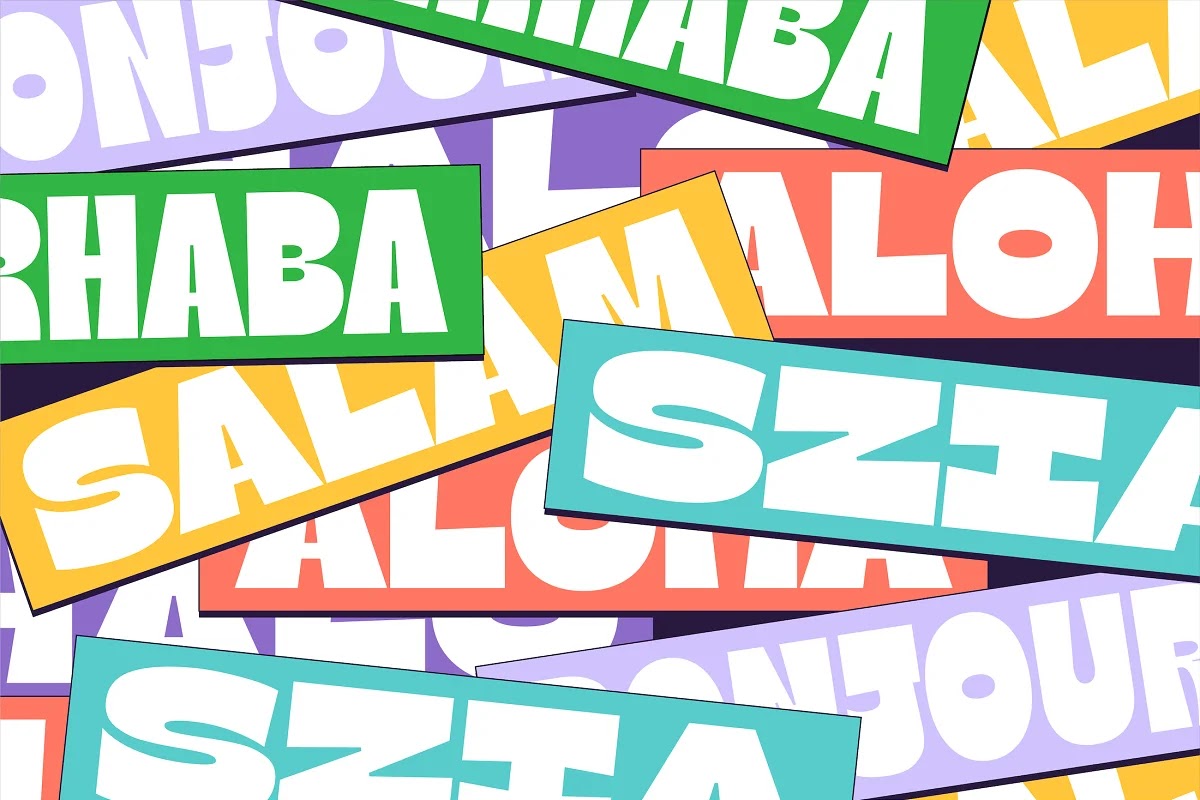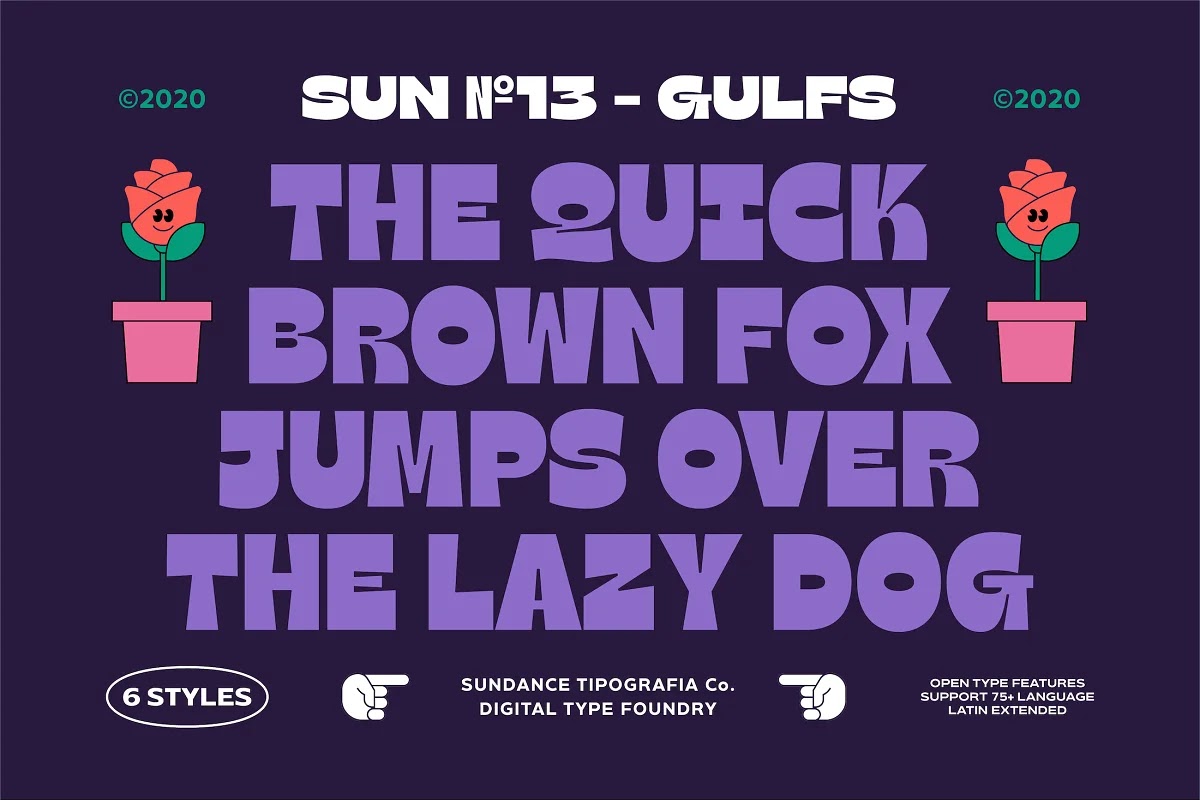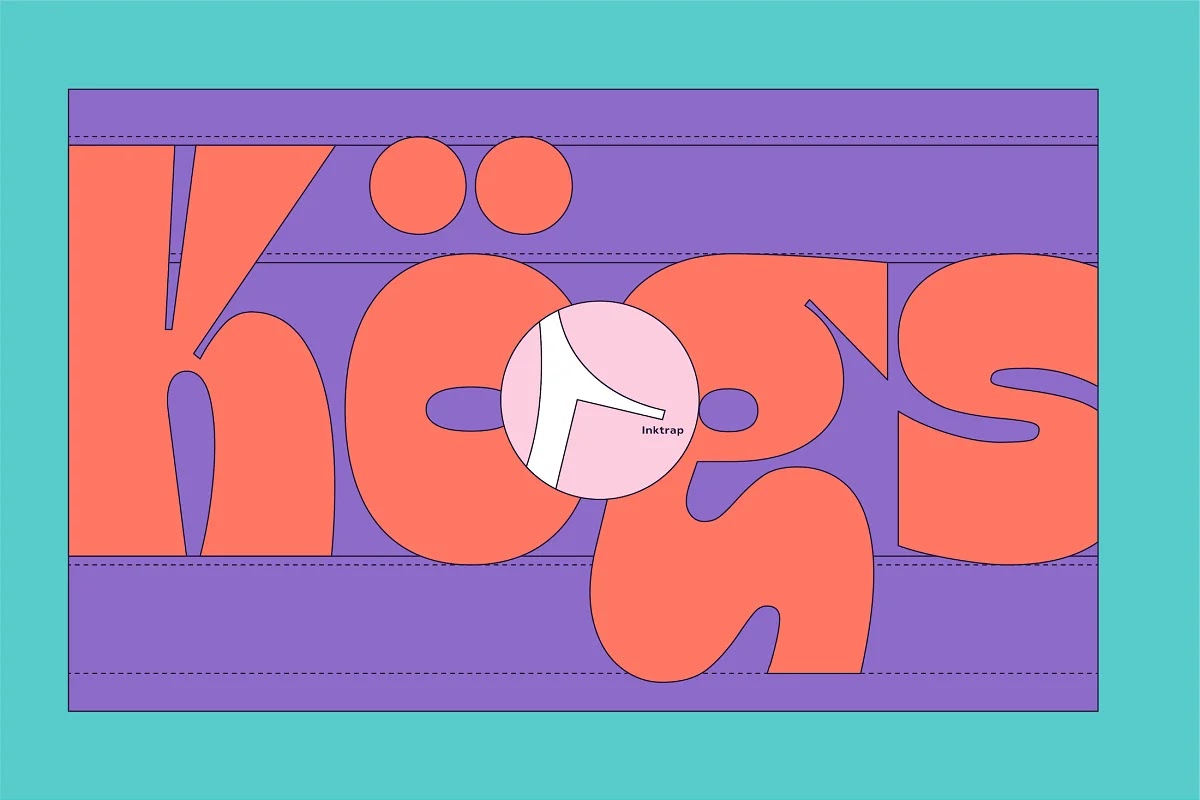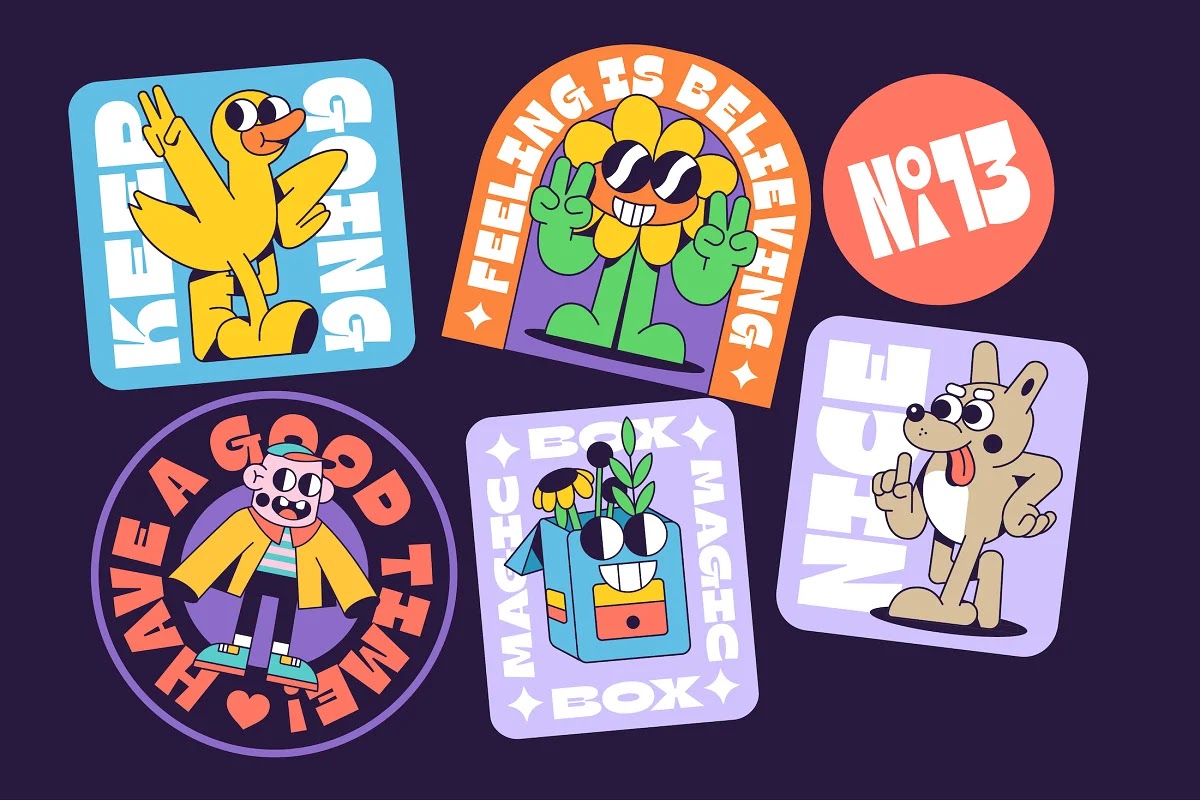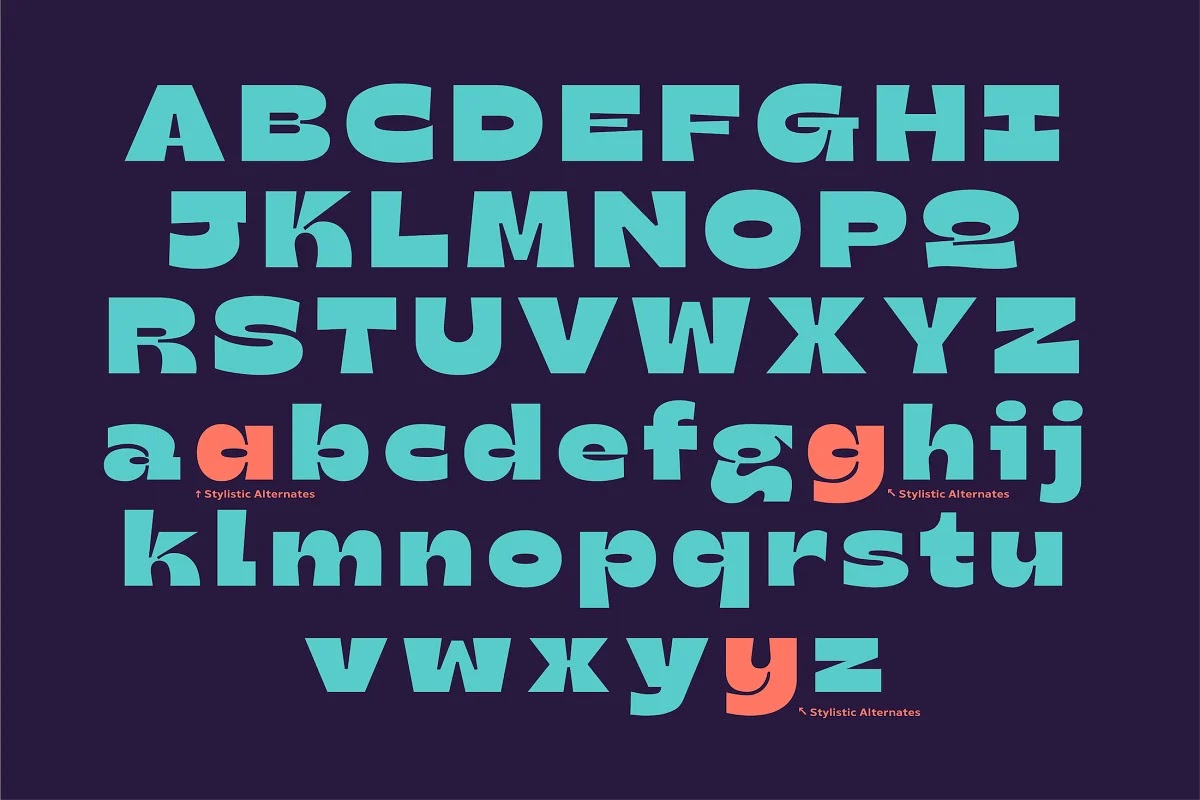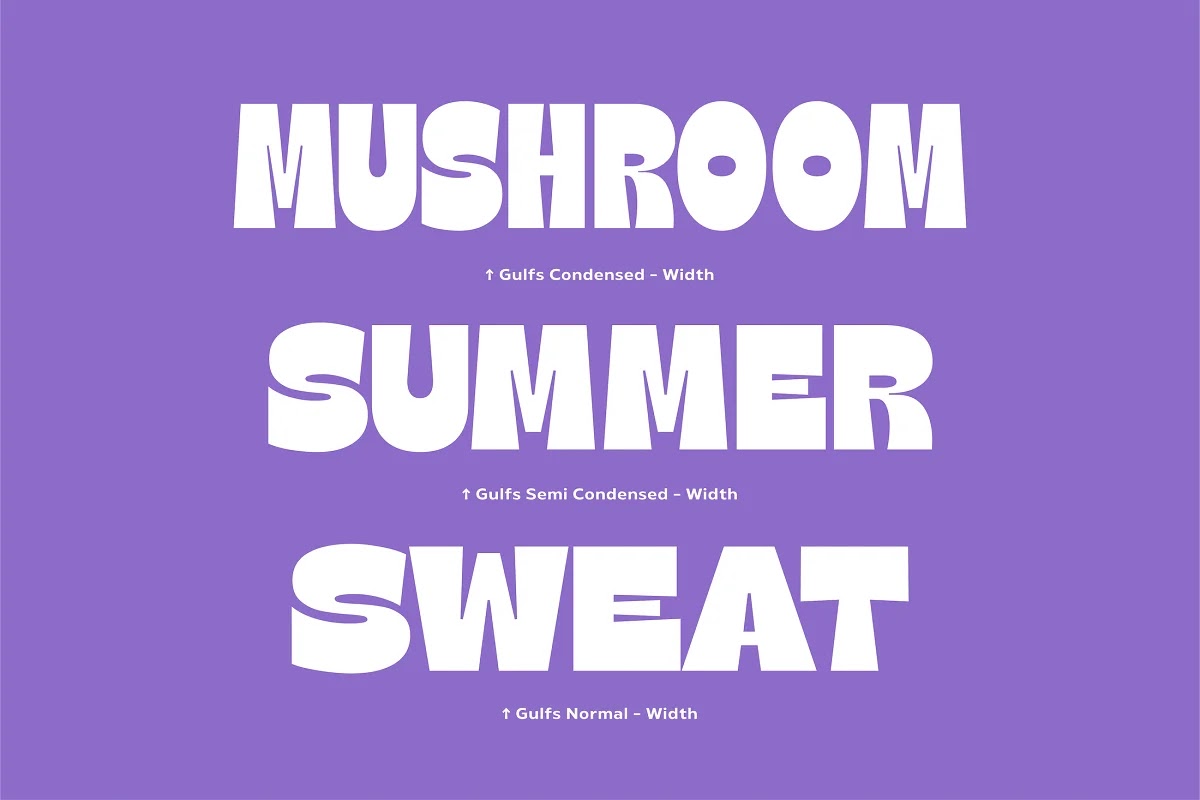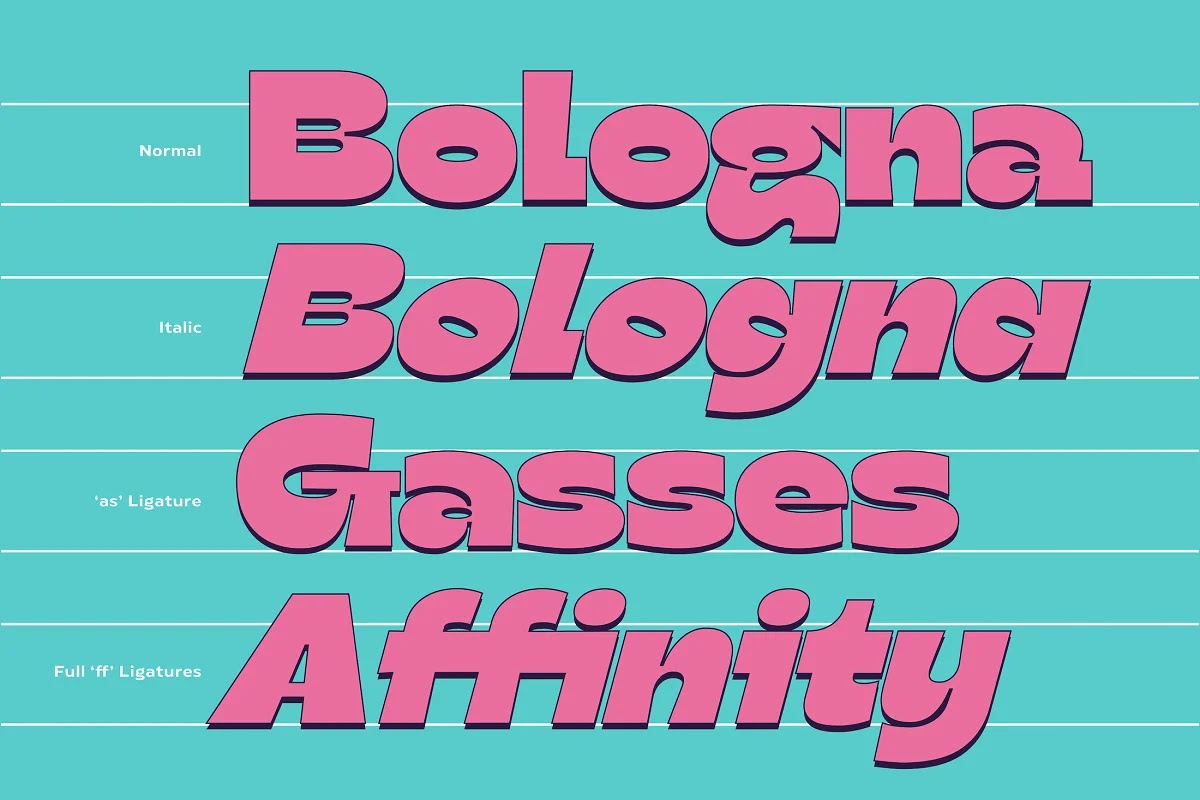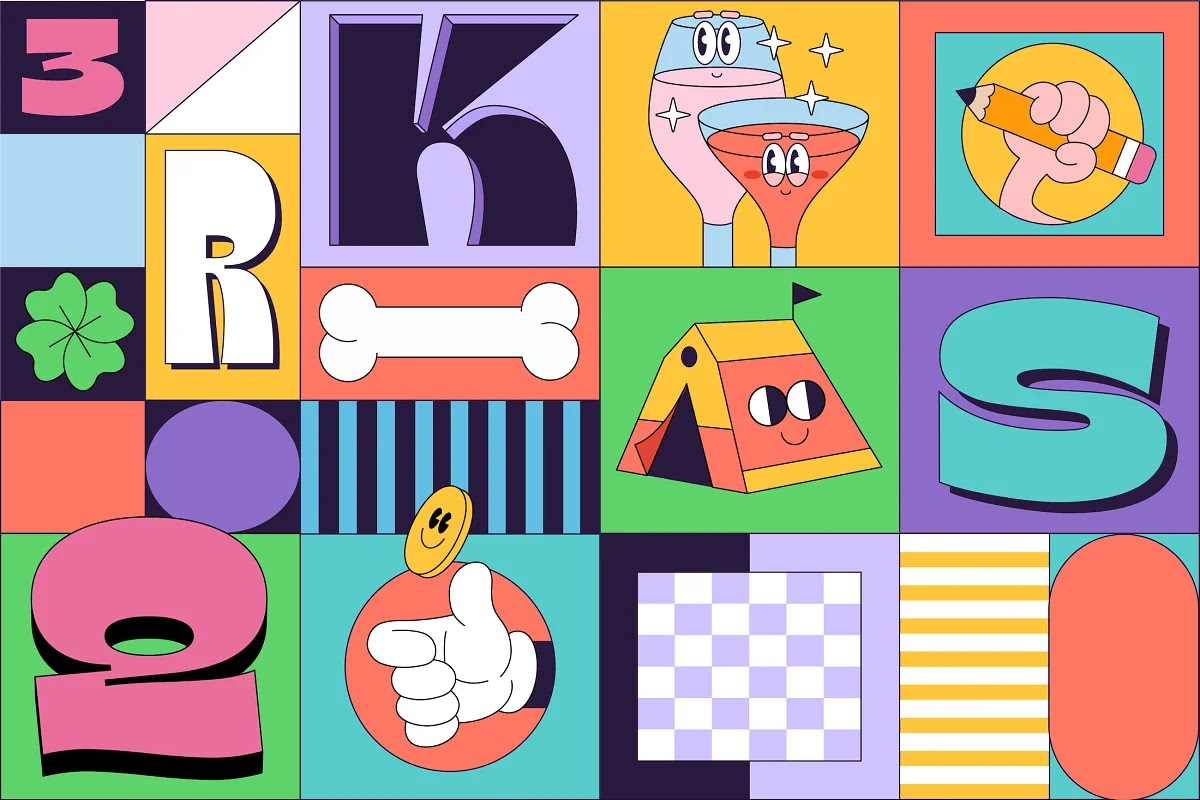
[Display] Gulfs Display Font Family (14 font)
Gulfs Display lấy cảm hứng từ truyện tranh và phim hoạt hình vui nhộn của thập niên 90. Font chữ vui nhộn này có 6 width: condensed, semi condensed, normal, semi expanded, expanded và extra expanded. Font chữ này có thể được sử dụng cho các thiết kế hiện đại và cổ điển, cũng có thể dễ dàng ghép nối với một số yếu tố đồ họa (Hình minh họa, Nhiếp ảnh) phông chữ này hoàn hảo cho Biểu trưng, Thương hiệu, Tiêu đề và Bao bì.